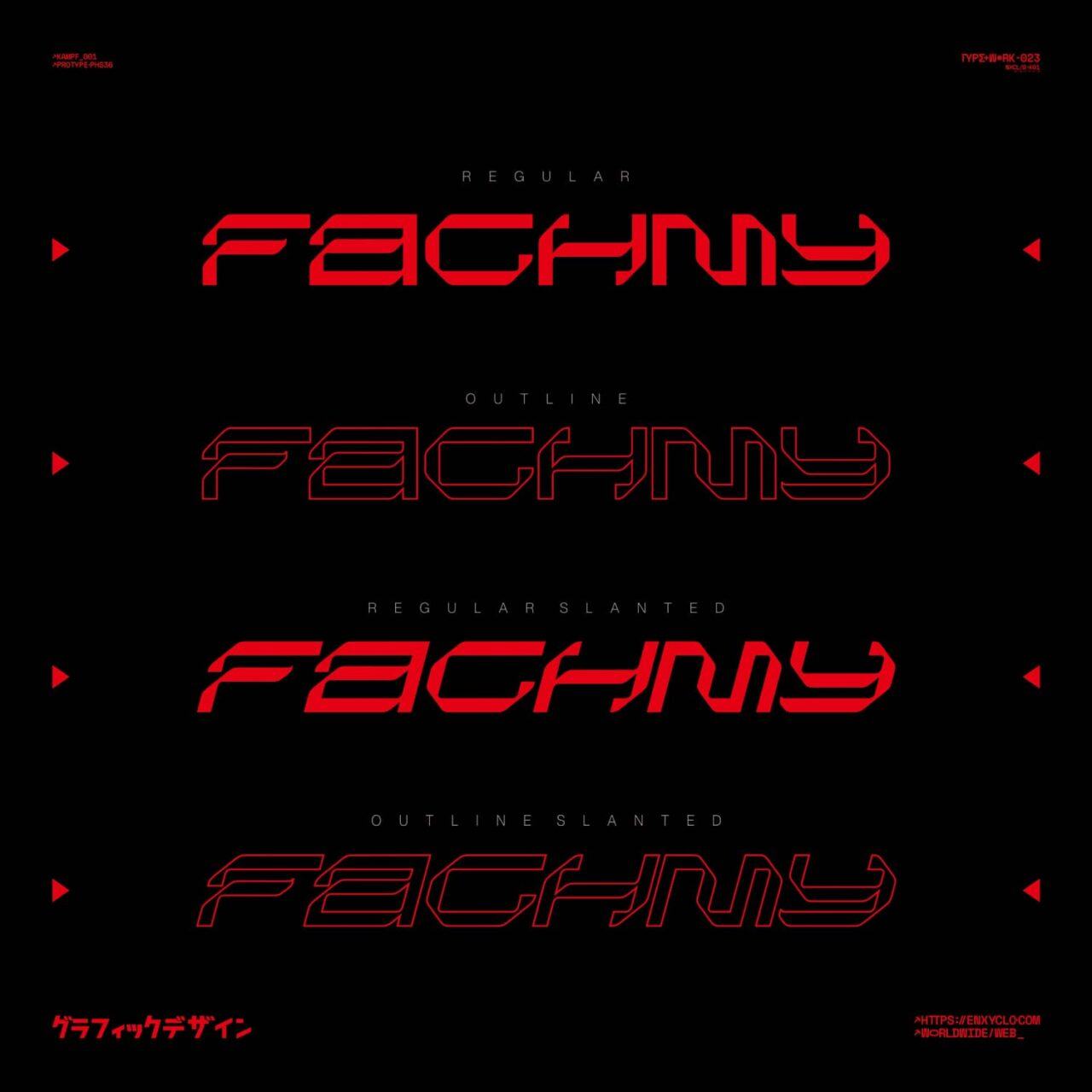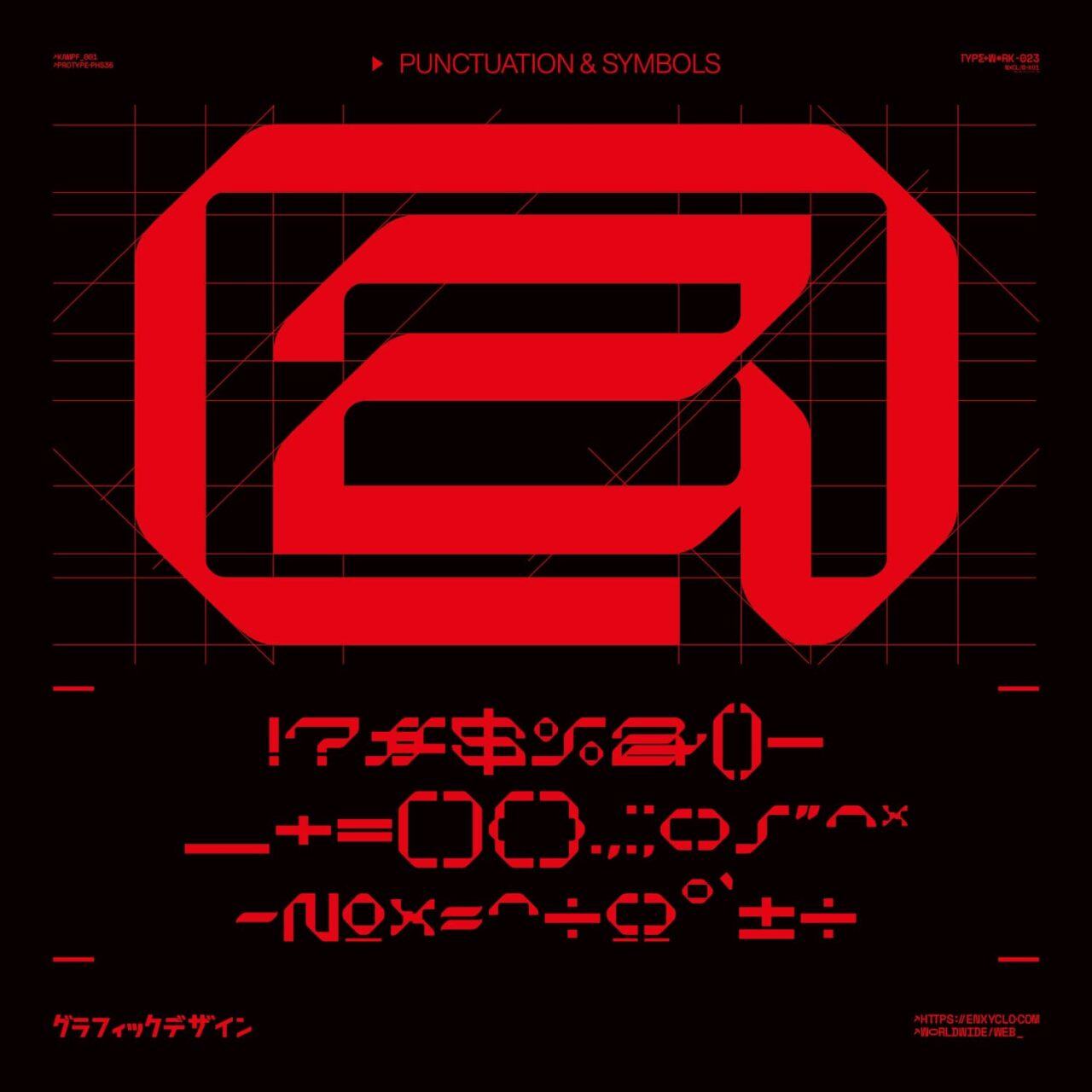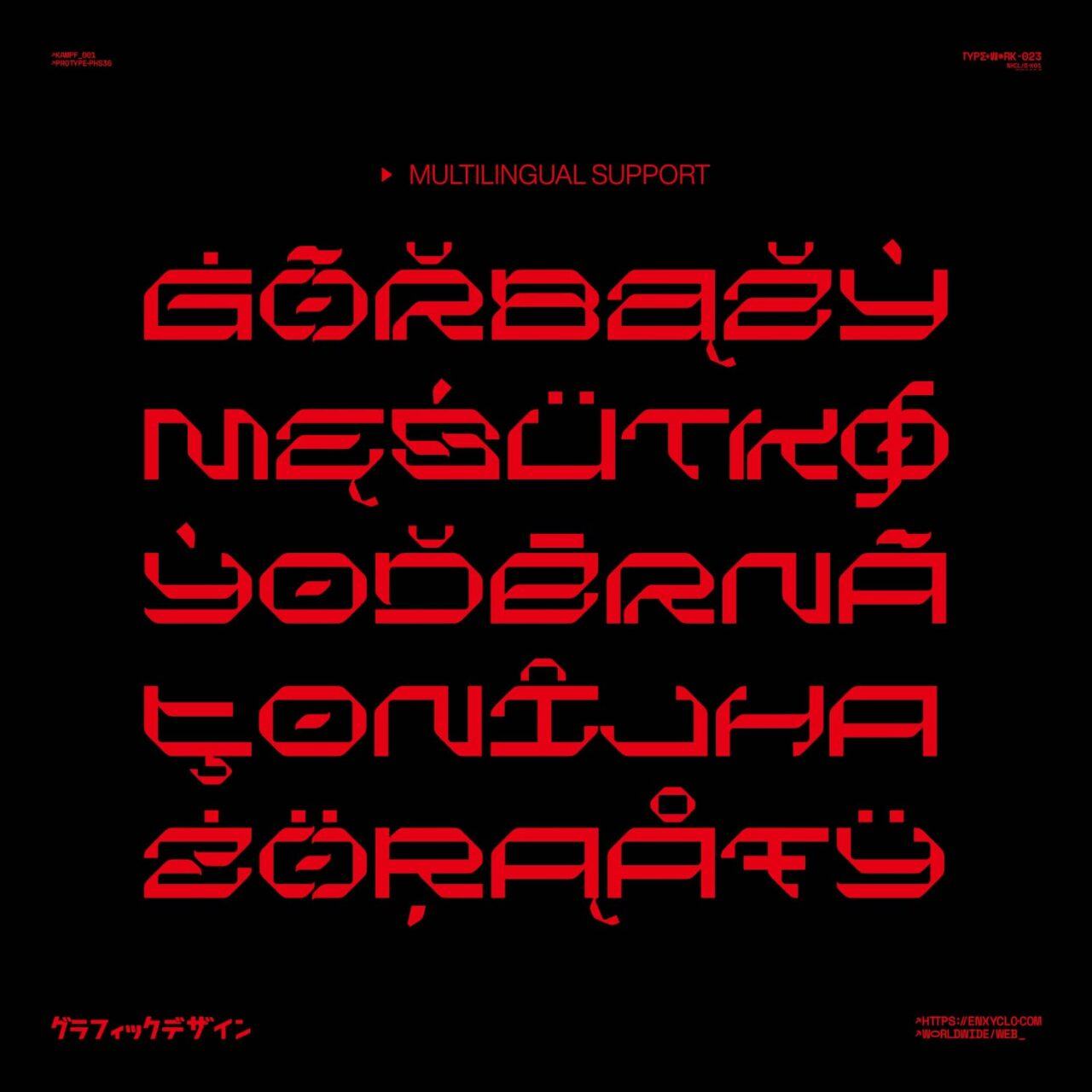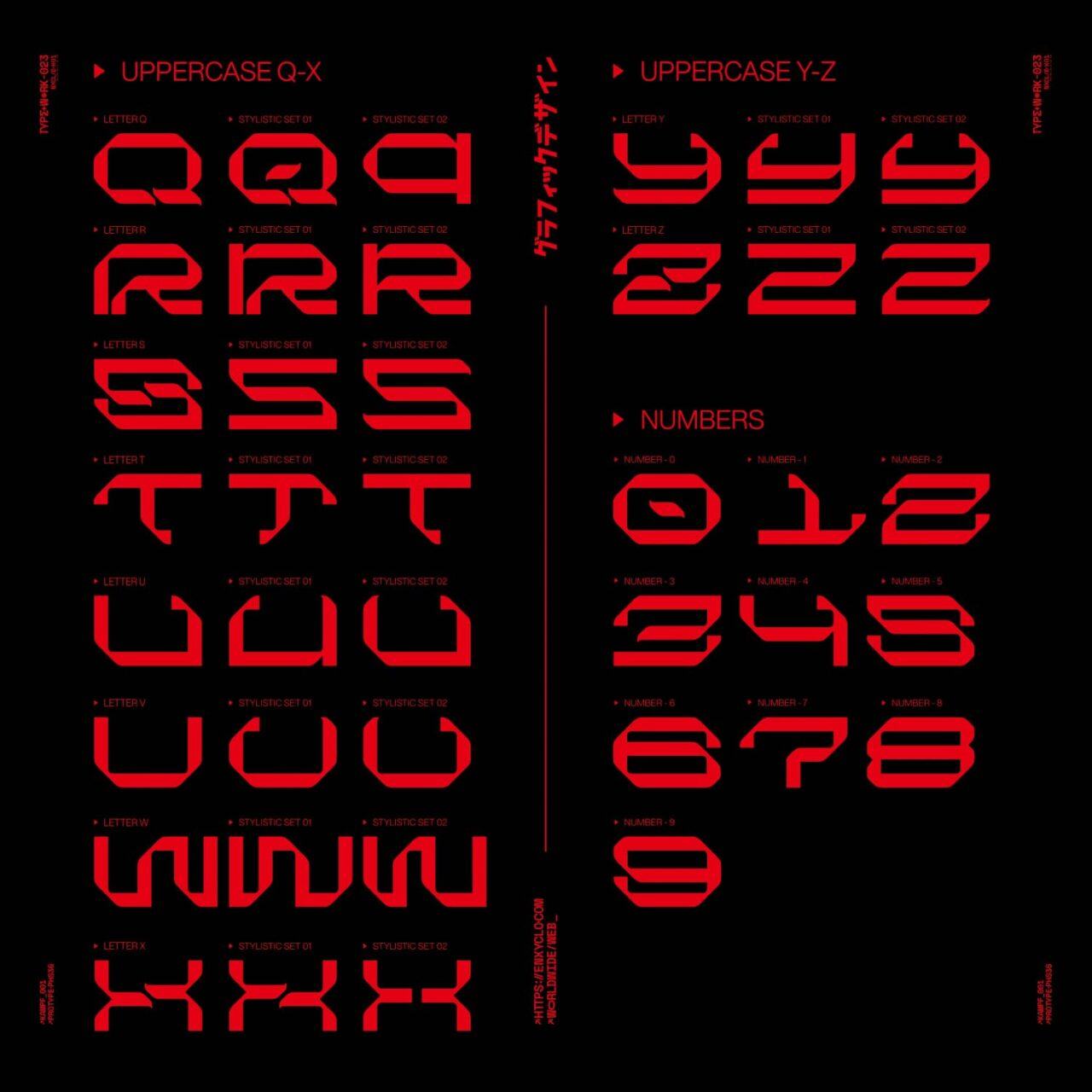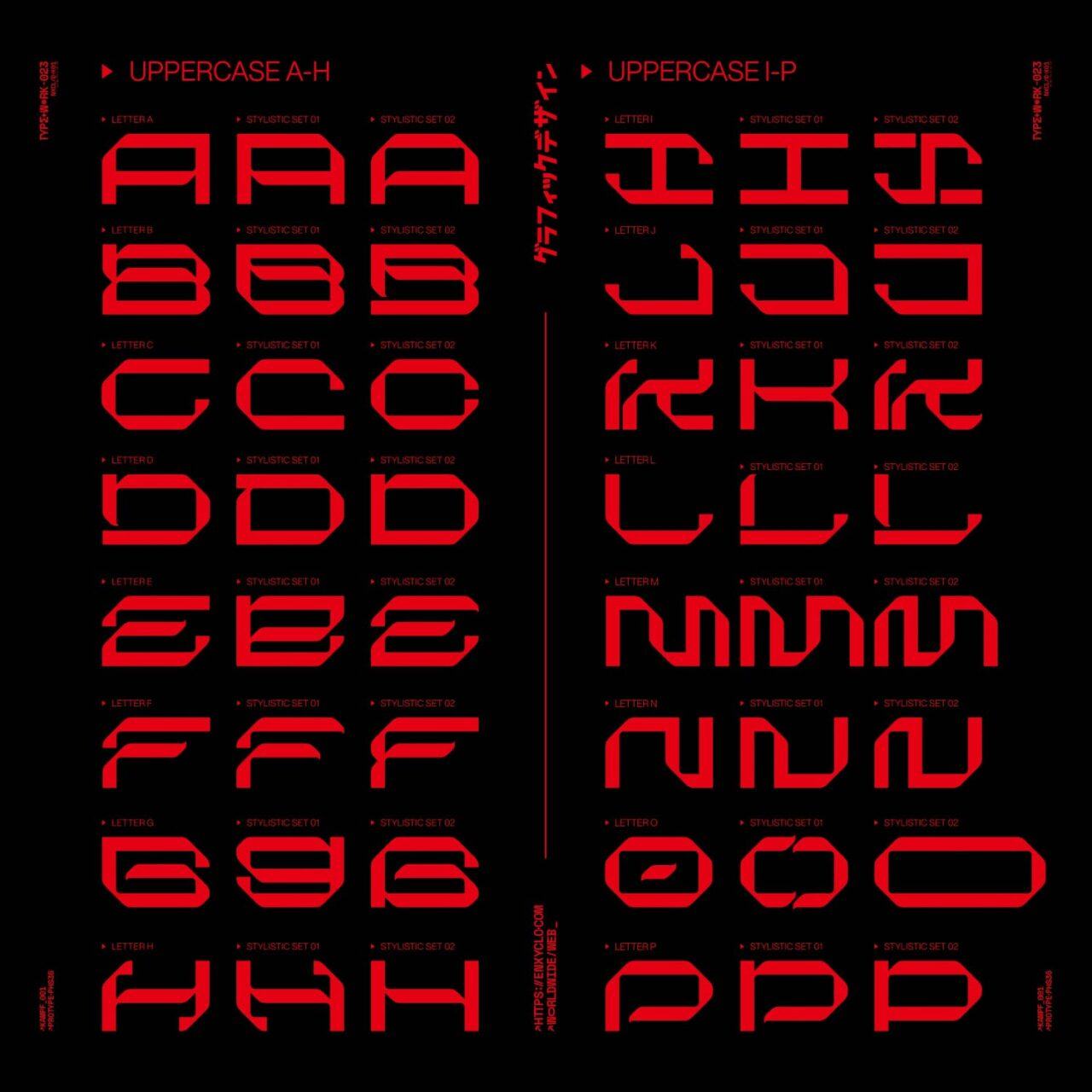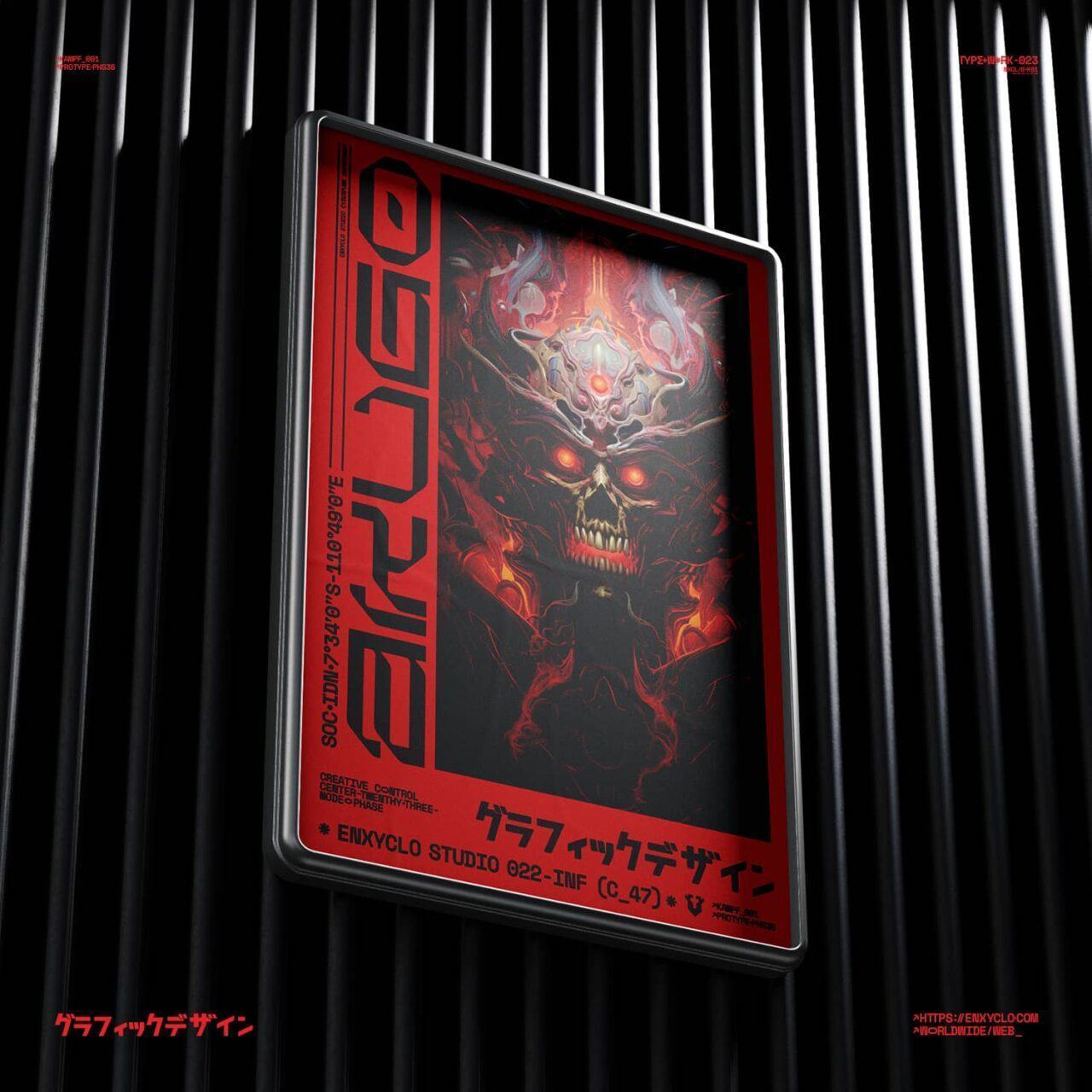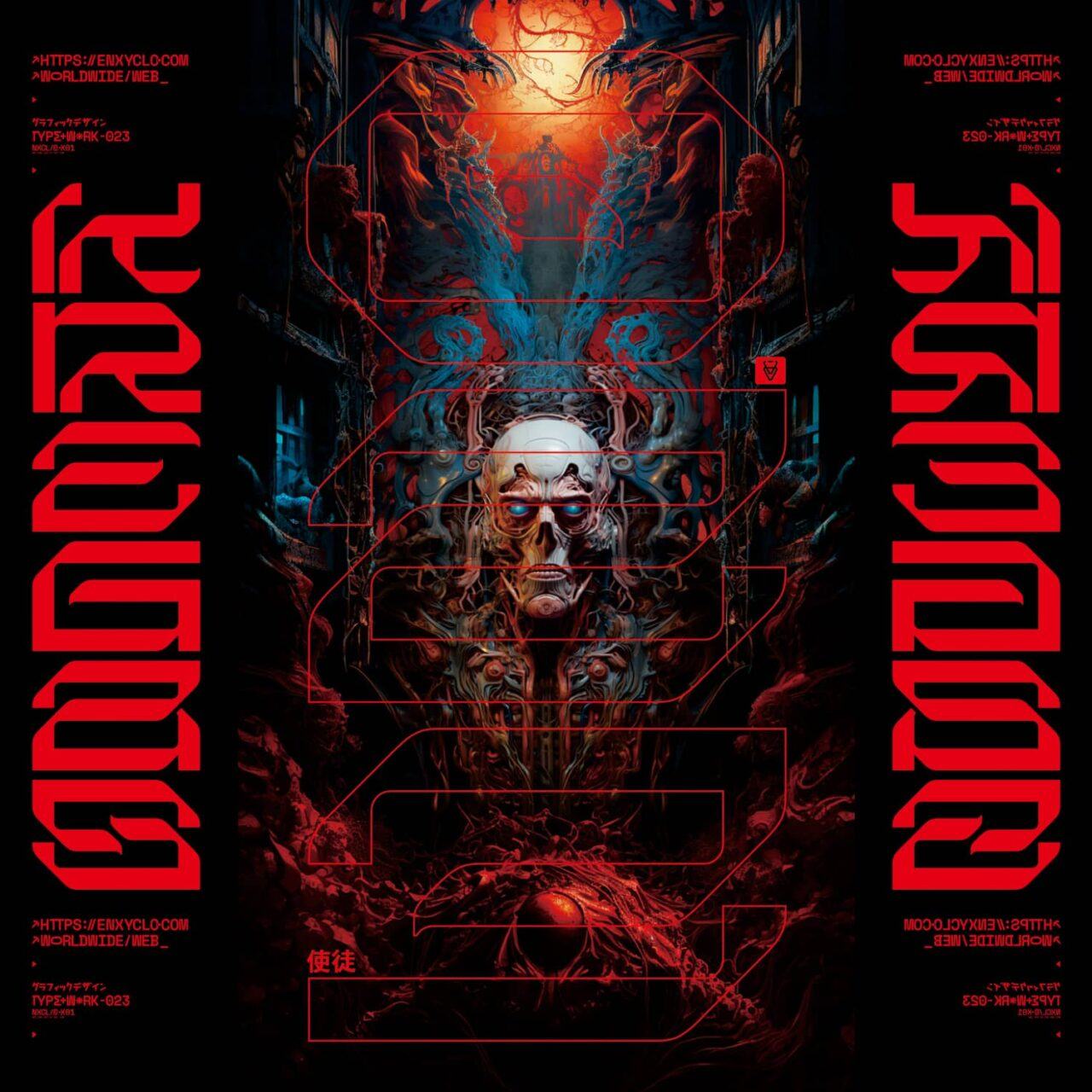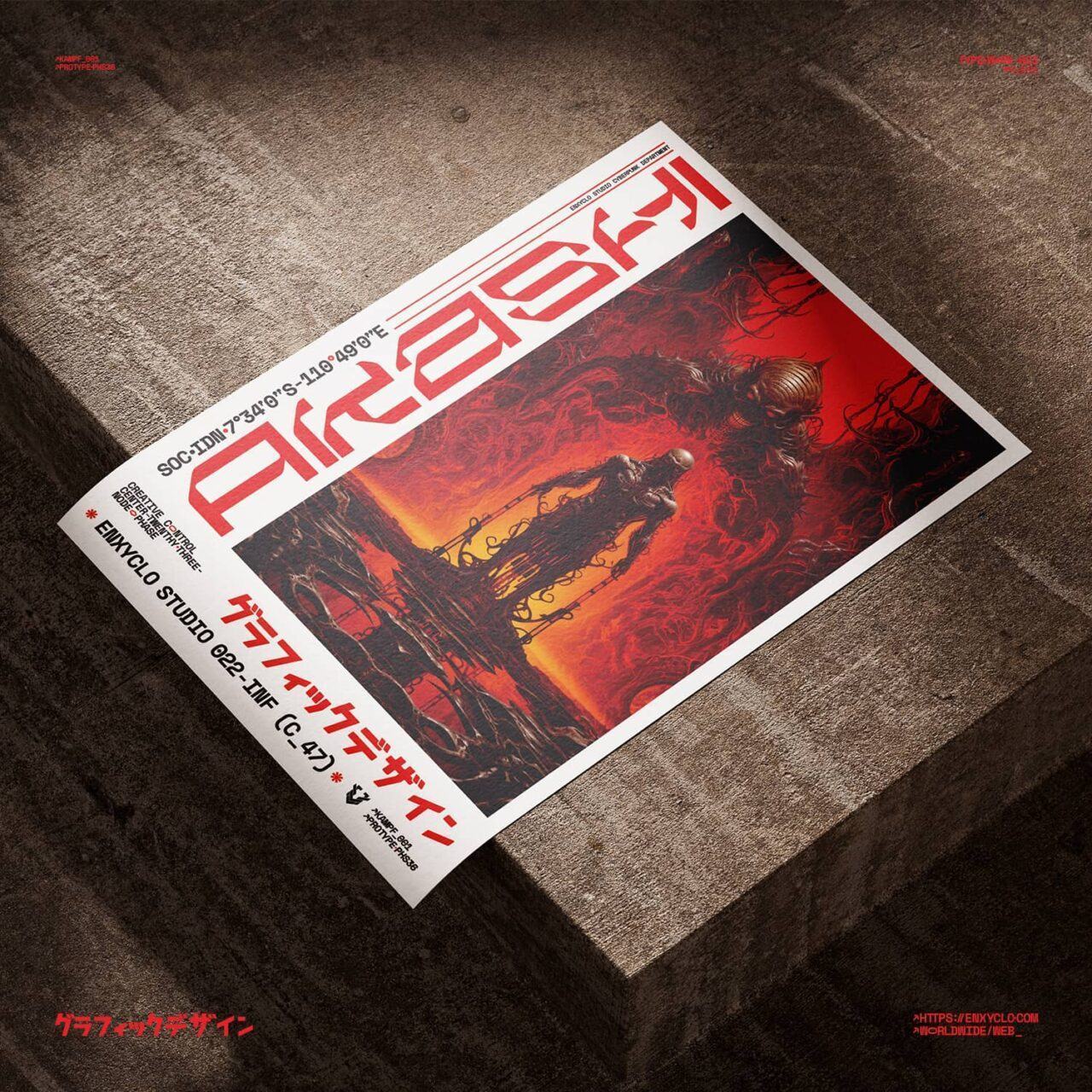
Giới thiệu NCL KEGAS, một phông chữ kỹ thuật tương lai cyberpunk đặc biệt có 4 kiểu – Thông thường, Nghiêng, Đường viền và Đường viền nghiêng. Bắt tay vào hành trình sáng tạo, nơi tính thẩm mỹ tương lai kết hợp với sự đổi mới, khiến các dự án của bạn thực sự nổi bật. Cho dù đó là quần áo, áp phích thủ công hay thiết kế logo, NCL KEGAS đều thêm nét tinh tế độc đáo và nét đặc biệt.
- 4 kiểu: Thông thường, nghiêng, phác thảo, phác thảo nghiêng
- Chứa 440 Glyph cho mỗi kiểu và 1760 Glyph cho tổng số
- Chữ in hoa chữ thường
- Chữ số, dấu câu và ký hiệu
- Bộ Phong Cách 1 & Bộ Phong Cách 2